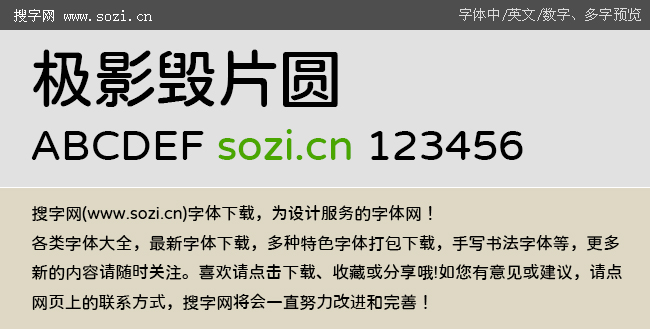
極影毀片圓
搜字網(wǎng)給大家提供一款極影毀片圓中文字體下載,極影毀片圓是本字體以jf open粉圓為底本,使用江城圓體3.0、獅尾圓體SC作為增補(bǔ),補(bǔ)全了Unicode的中日韓統(tǒng)一表意文字,并且根據(jù)通用規(guī)范漢字表,修正常用的簡體字的筆畫所整理而成的字體。免費(fèi)供大家使用。適合應(yīng)用于藝術(shù)設(shè)計(jì)、平面宣傳設(shè)計(jì)、網(wǎng)頁設(shè)計(jì)、海報(bào)設(shè)計(jì)等應(yīng)用。